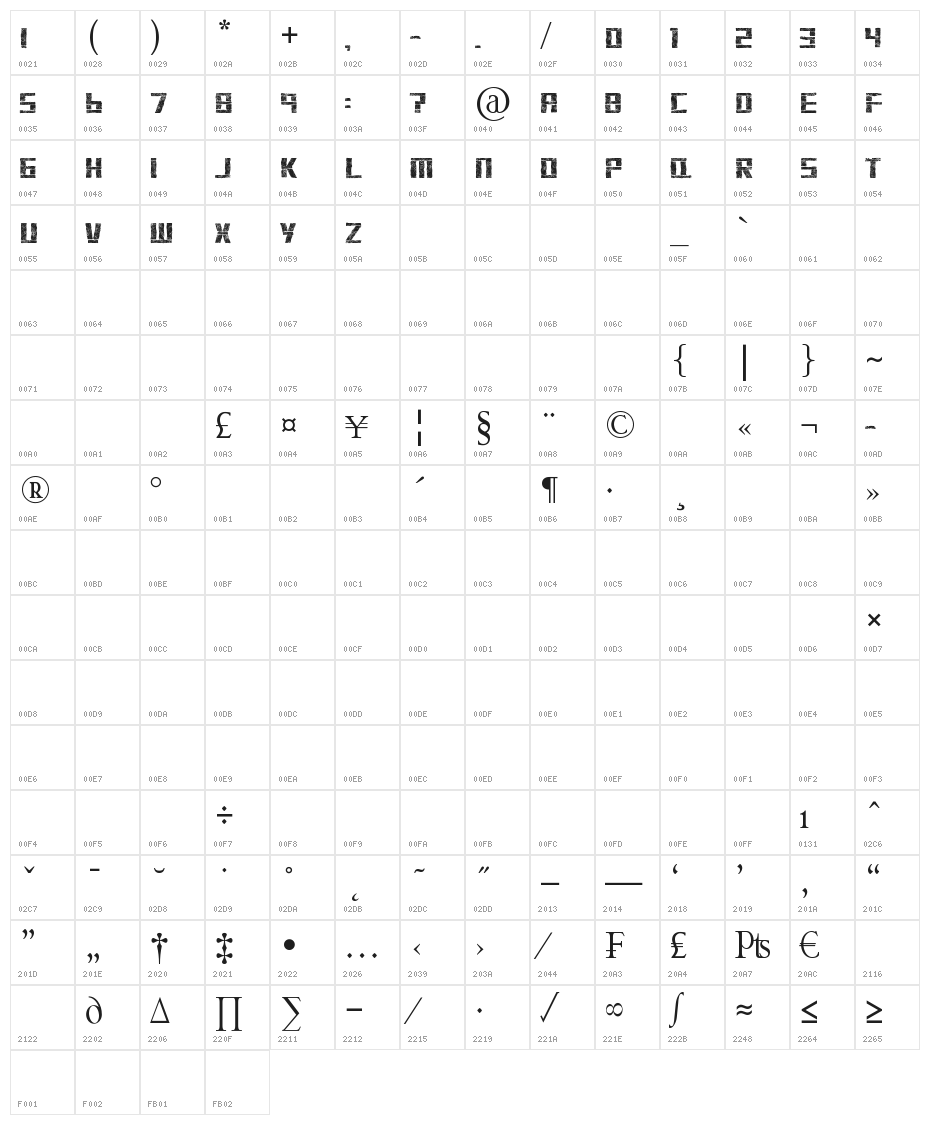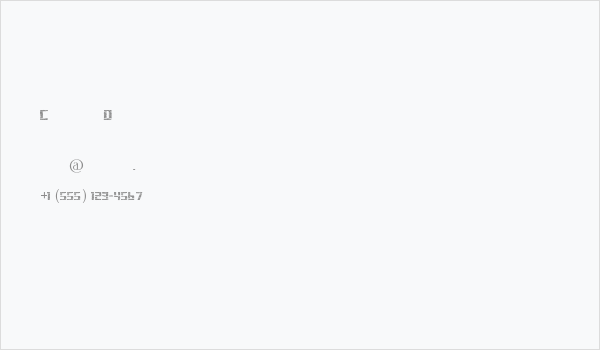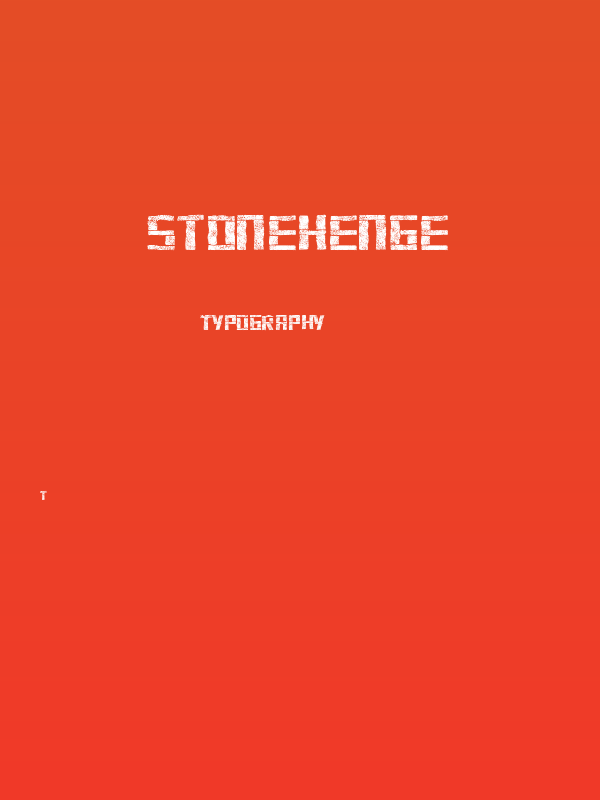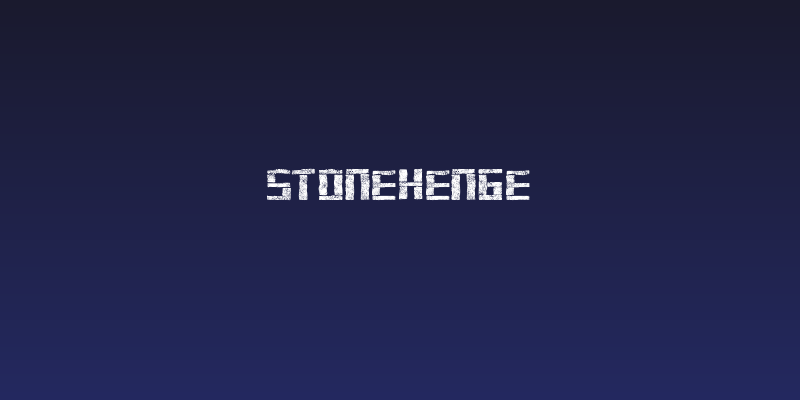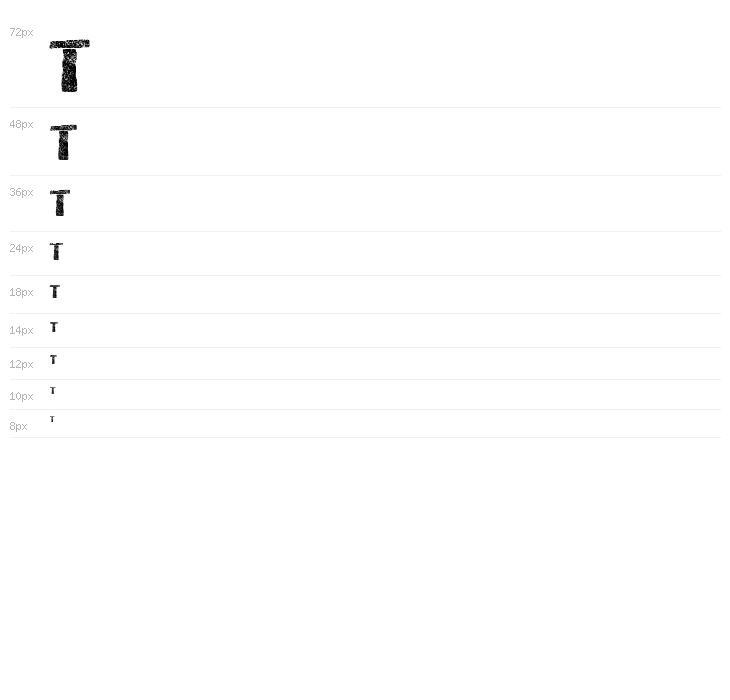
stonehenge Font
✎ Gothic
| Vorgeschlagene Projekte | Ideal for archaeological themes, historical documentaries, outdoor adventure branding, or rustic event invitations. |